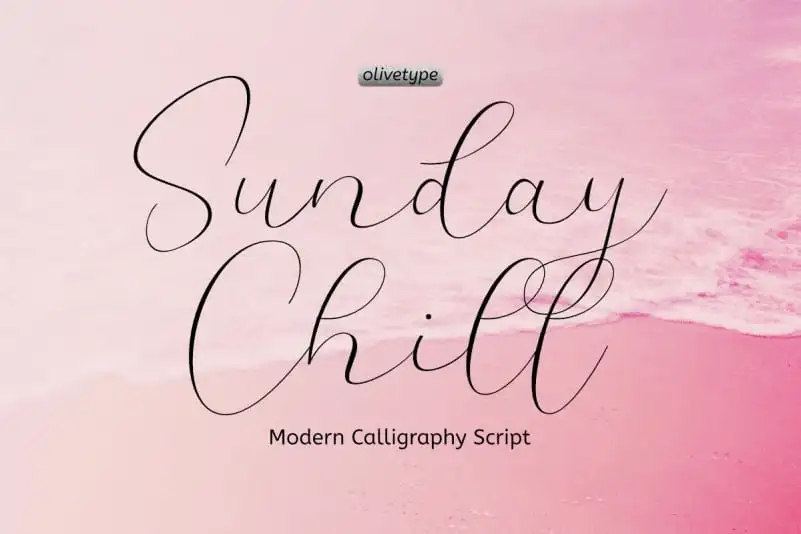
Sunday Chill Script Font – Download Grátis
A fonte ‘Sunday Chill Script Font’ é uma elegante e feminina tipografia moderna que honra a arte do xilográfico com sua delicadeza moderna, criada por Olivetype. Essa stunning handwritten font apresenta linhas suaves e variadas em baseline, proporcionando um estilo de homenagem ao chamado clássico. É perfeita para uma página de download que exalte a beleza dos xilográsicos de maneira sofisticada, oferecendo agradáveis caracteres e alternativas incríveis. Com esse design, você pode decorar notícias diarias, cartas pessoais ou qualquer outra mídia onde desejar criar um toque especial, combinando o elegante com o feminino na arte do texto.